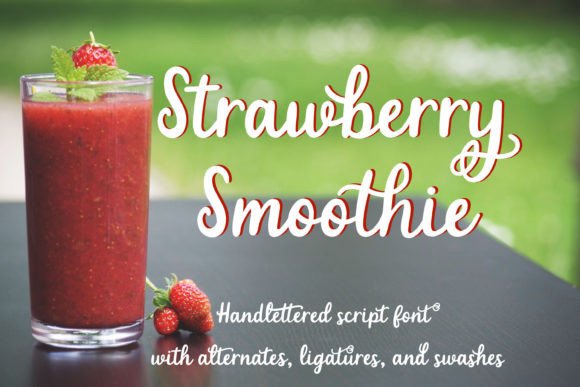
Strawberry Smoothie
Việc tìm kiếm các thành phần thiết kế phù hợp có thể là một thách thức, nhưng Strawberry Smoothie cung cấp một bộ sưu tập đặc biệt giúp nâng tầm công việc của bạn ngay lập tức.
Được chế tác với độ chính xác cao, Strawberry Smoothie cung cấp các vector sạch, kiểu chữ mượt mà và giấy phép thương mại để bạn yên tâm.